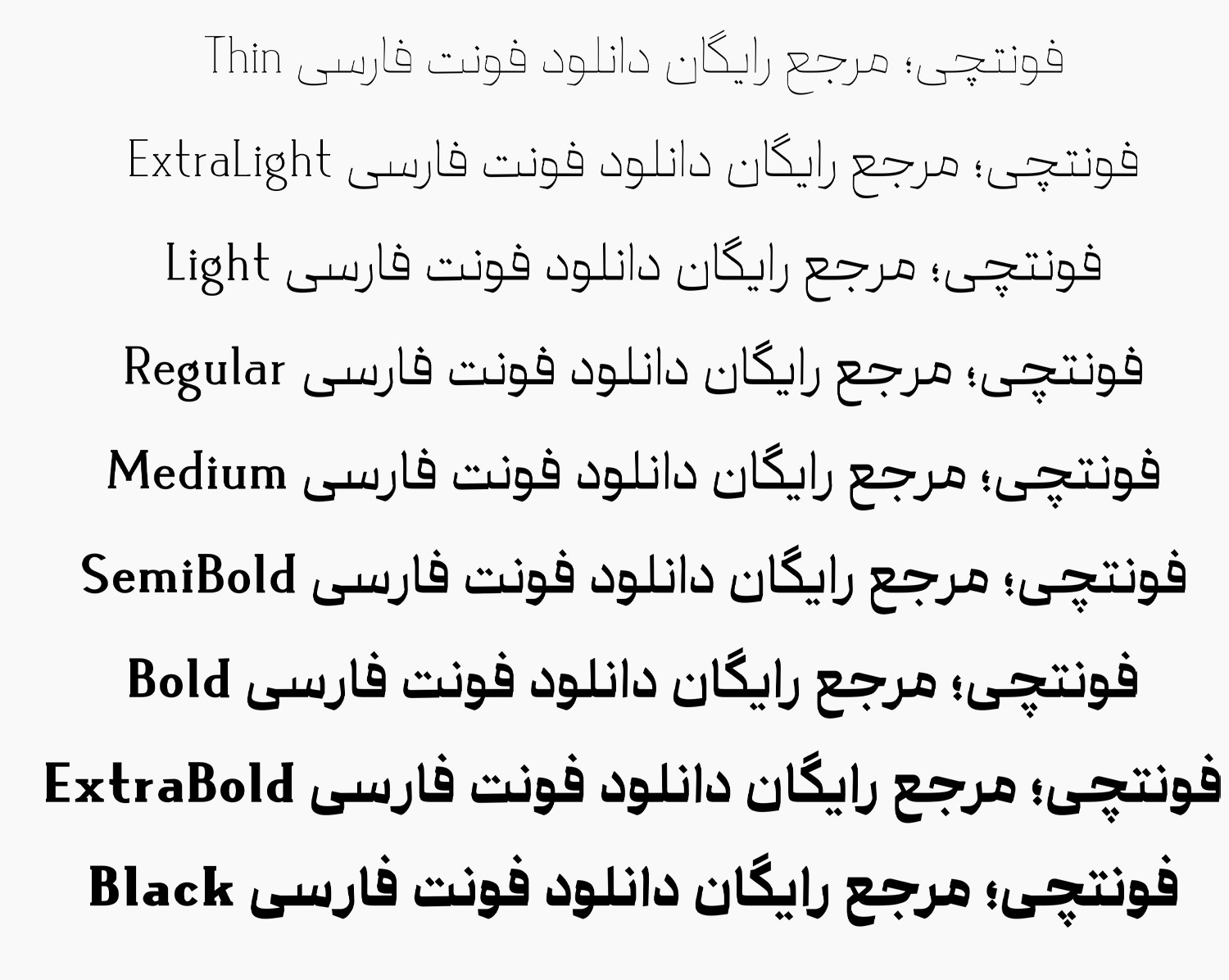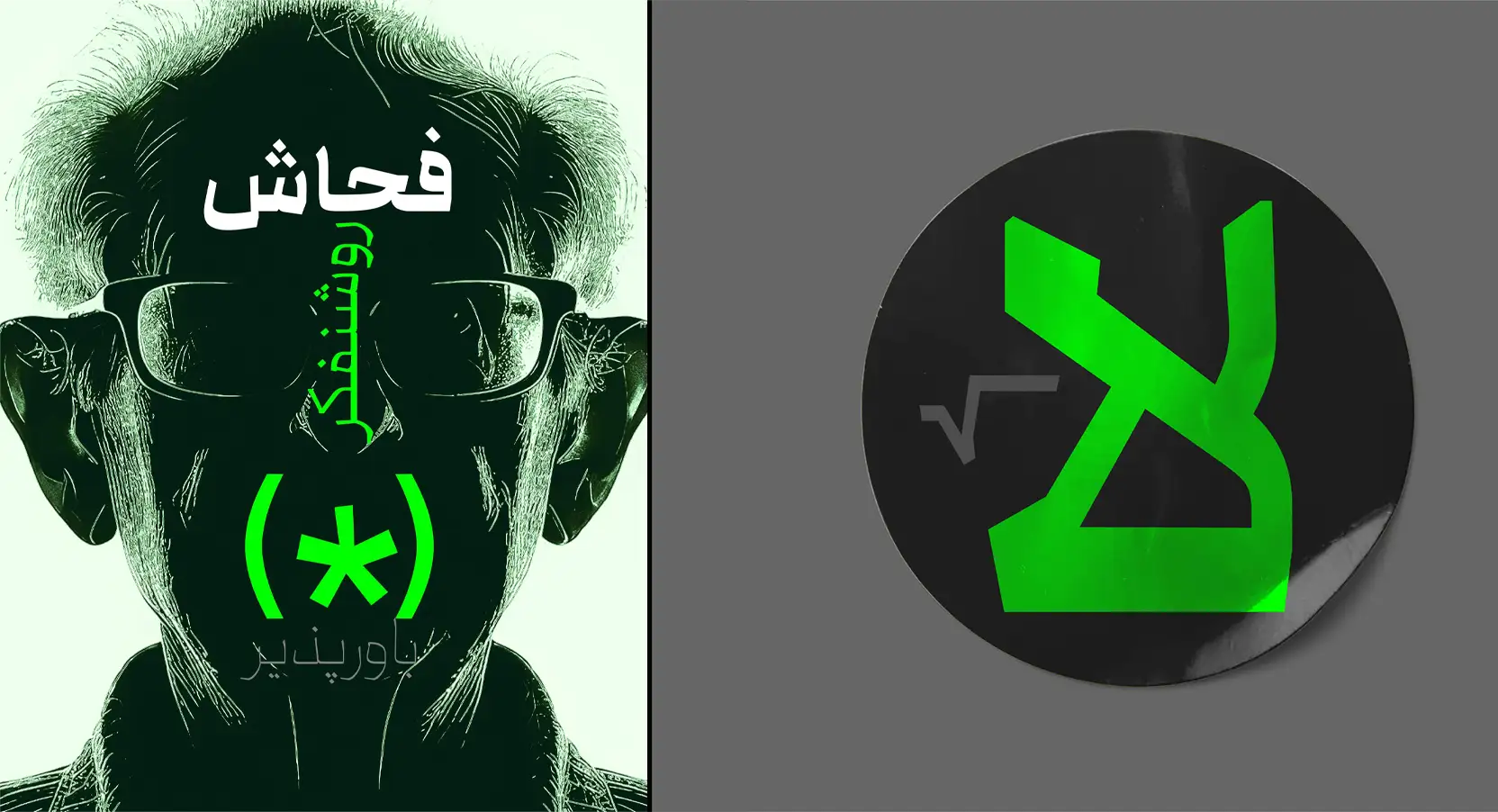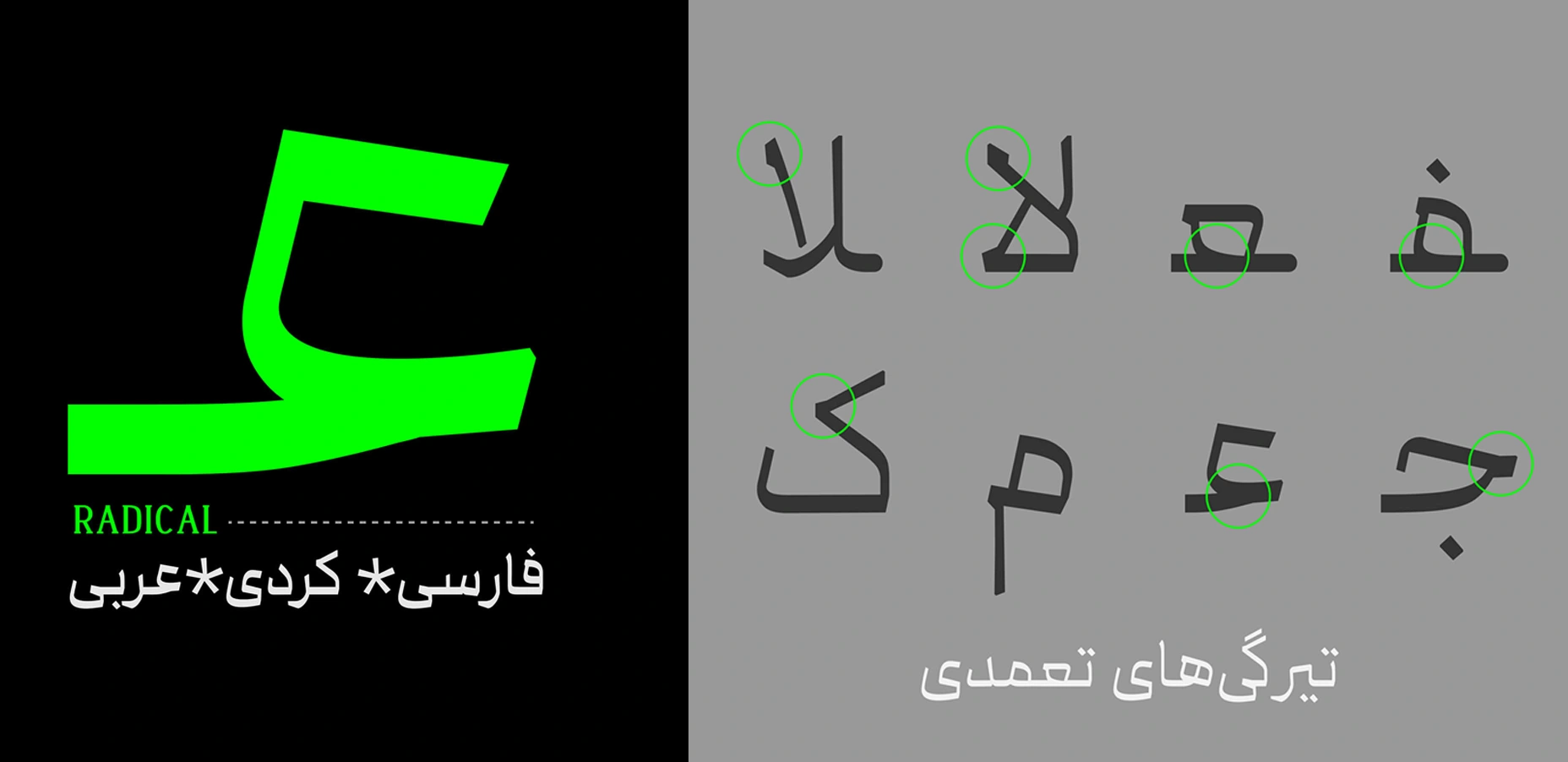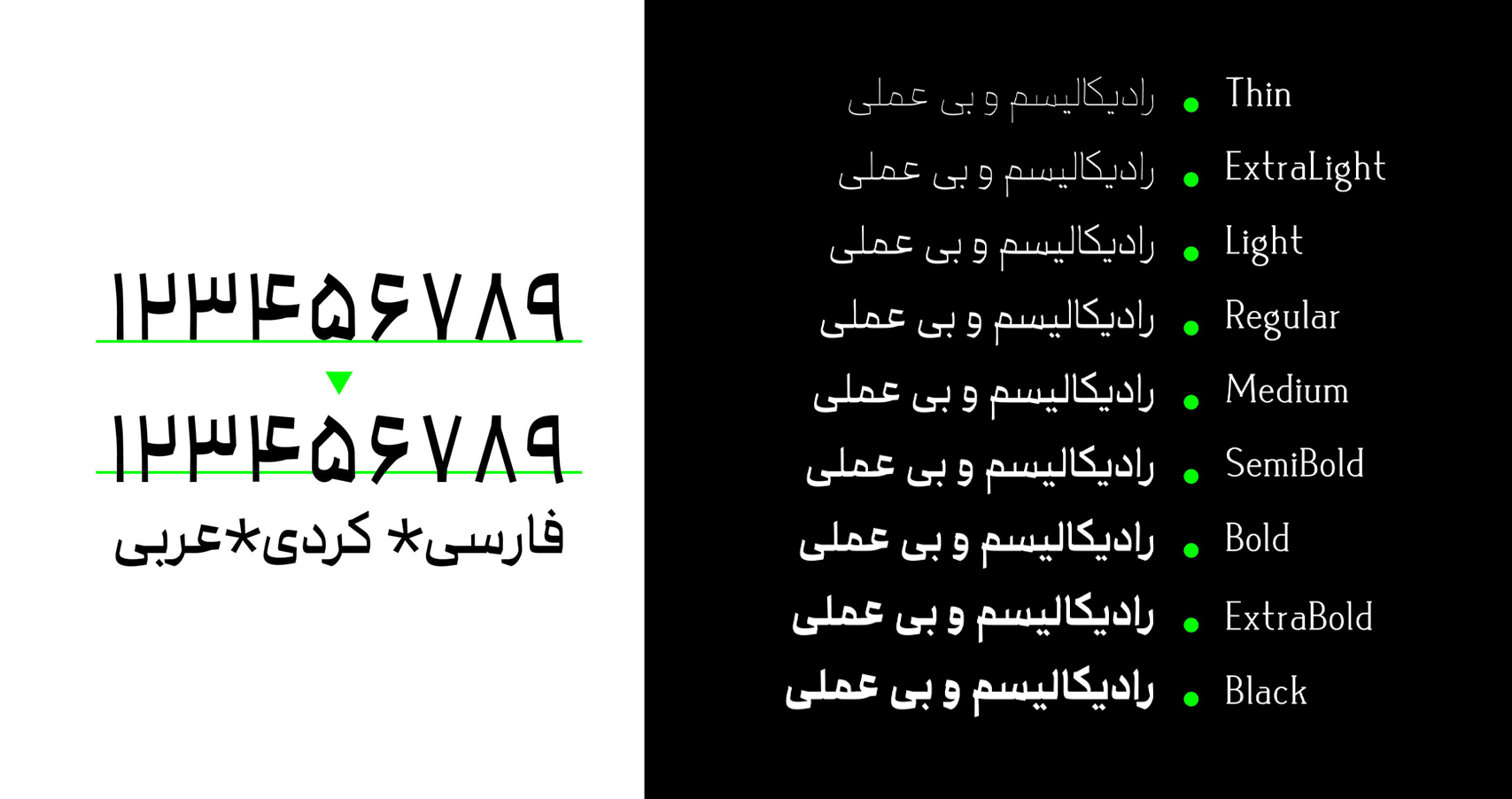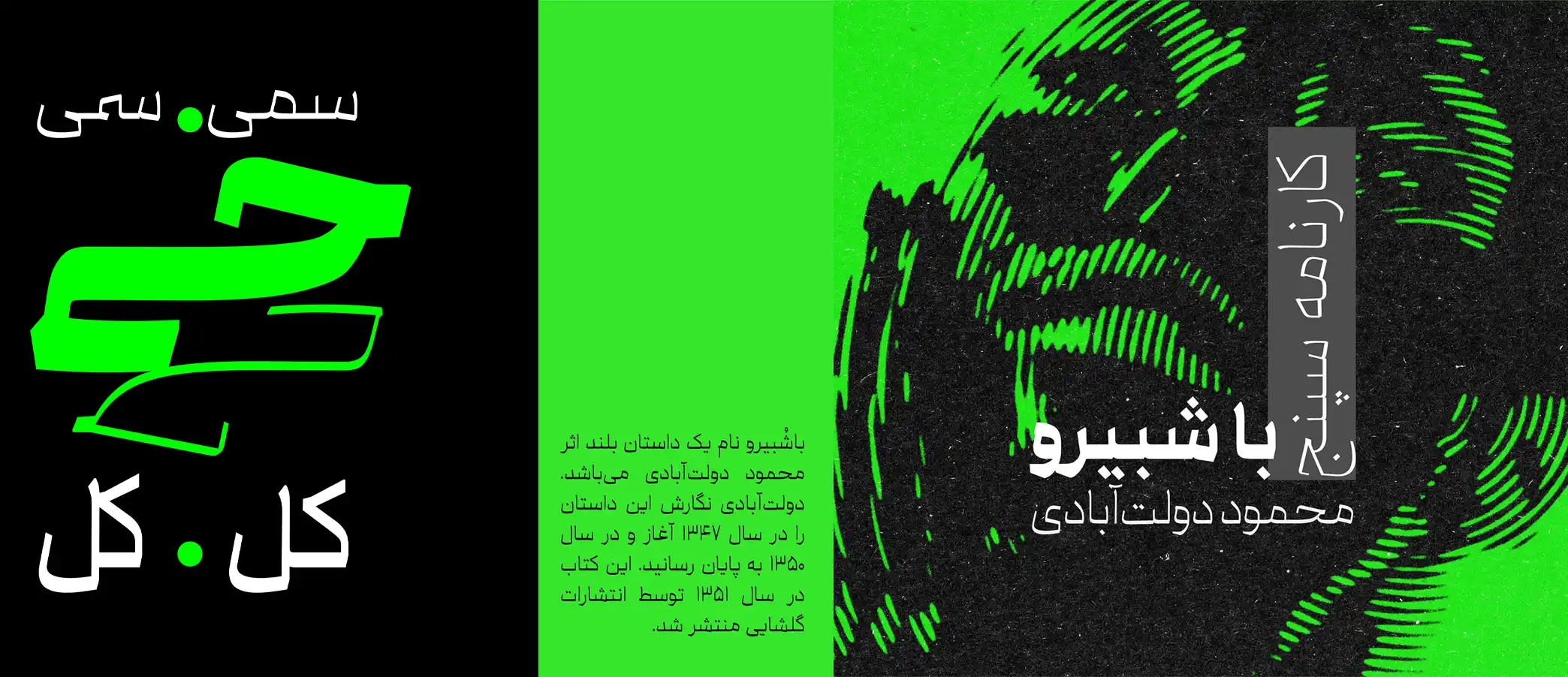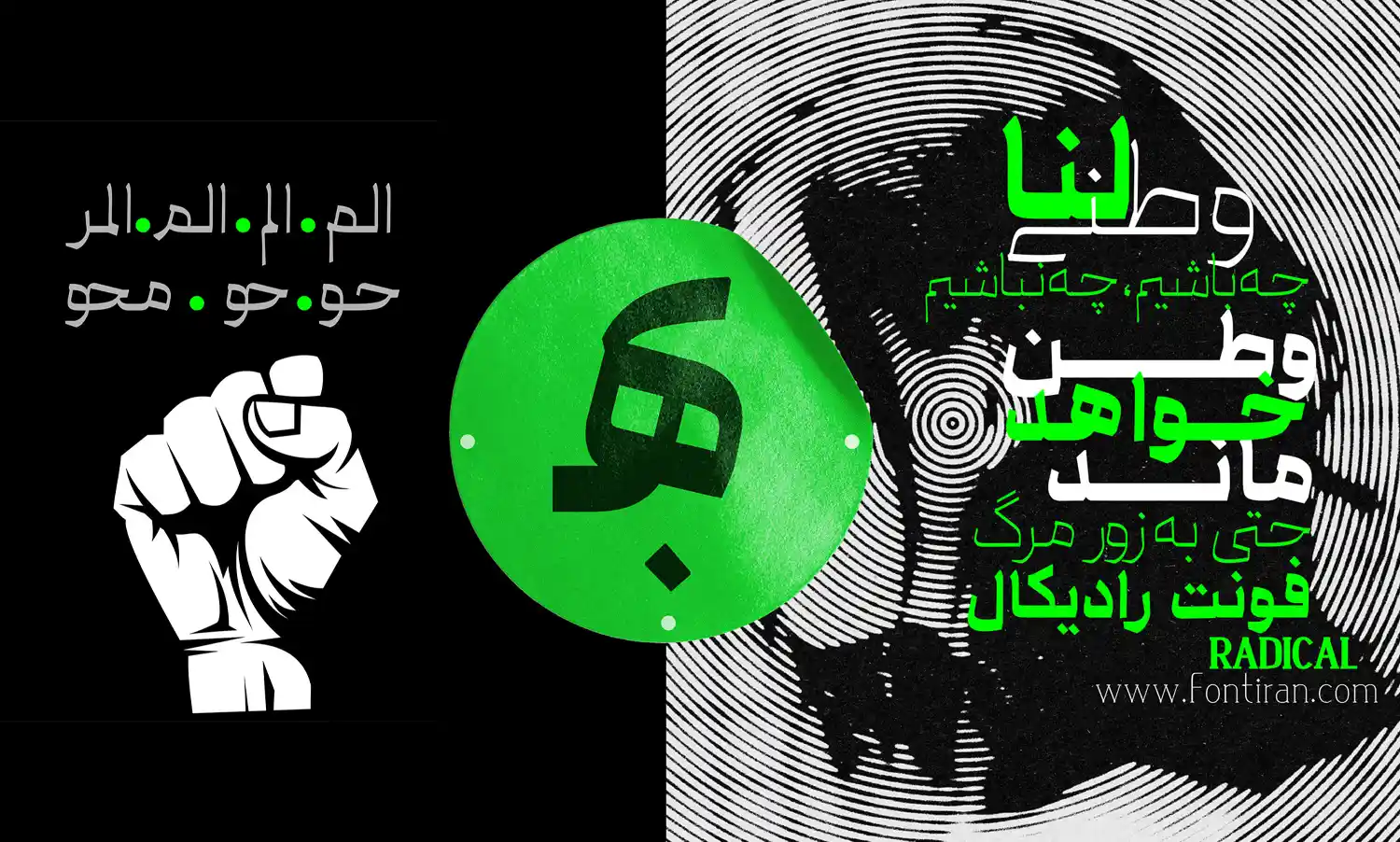
فونت رادیکال (Radical)
| طراح | مهرداد نوتاش |
فونت رادیکال (به انگلیسی: Radical) از سری فونتهای هندسی است که ظاهری نزدیک به خط نسخ دارد. این فونت که از ۹ وزن نازک تا سیاه را پشتیبانی میکند، برای استفاده در عناوین، تبلیغات، طراحی پوستر و کارهای گرافیکی انتخابی خارقالعاده است. فونت رادیکال رایگان نیست و در دو بسته مجزا با تنوع وزنی گوناگون قابل خریداری است.
مهرداد نوتاش این فونت نمایشی را با تمرکز بر روی پشتیبانی از زبانهای فارسی، عربی و کردی طراحی کرده است. ساختار فونت بهگونهای است که ضخامت حروف در خط کرسی دو برابر بوده و خود را بیشتر نشان میدهد. در ادامه با نقد و بررسی تخصصی این فونت جدید فارسی همراهمان باشید.
رادیکال (Radical) در نسخه اولیه خود با ۹ وزن (Thin، Extralight، Light، Regular، Medium، SemiBold، Bold، ExtraBold، Black) عرضه شده است.
طراحی فونت رادیکال بر پایه هندسه استوار است و شباهتهایی به خط نسخ سنتی دارد، اما ظاهر مدرن و جسورانه دنیای امروز در آن تنیده شده است. تنه حروف ضخامتی تقریبا دو برابر حد معمول قلمهای استاندارد را داراست؛ همین امر ظاهری محکم و سنگین به حروف داده است، بهویژه در خط کرسی. گویی طراح عمدا حروف را در چارچوب کلاسیک نسخ اسیر کرده، اما با فاصله گرفتن از این چارچوب، حرکات قلم آزادتر، نامنظمتر و «رادیکالتر» میشود.
این رویکرد، فونتی ایجاد کرده که تیرگیهای عمدی (مانند سایههای مصنوعی در منحنیها) و ضخامتهای غیرمعمول (مثل پهنای متغیر در استروکها) را به عنوان ویژگیهای کلیدی خود برجسته میکند. نتیجه، یک تایپوگرافی منحصربهفرد است که از یکنواختی فونتهای رایج فارسی فاصله میگیرد و تمایزی بصری قوی ایجاد میکند.
لحن فونت، «صریح، جدی و رو راست» است. از اینرو برای استفاده در محیطهایی برای بیان مستقیم و بیپرده ایدهها مناسب است. این لحن از طریق با افزایش کنتراست در ضخامتها (به ویژه در وزنهای Bold و سنگینتر) و فرمهای هندسی تیز (مانند زوایای حاد در حروف مثل “ک” یا “ر”) تقویت میشود.
در مقایسه با فونتهای نمایشی دیگر فارسی مانند ایران سنس یا وزیر، رادیکال نرمی کمتری داشته و بیشتر ظاهری تهاجمی از خود نشان میدهد. شباهت به نسخ آن را برای پروژههای فرهنگی و سنتی مناسب میکند، اما رادیکالیسمش (مانند انحرافات عمدی از خط مستقیم در استروکهای افقی) آن را به ابزاری ایدهآل برای طراحیهای معاصر تبدیل میکند.
رادیگال؛ فونتی چند زبانه بر پایه حروف فارسی
عدم طراحی اختصاصی برای حروف لاتین (استفاده از فونت پیشفرض سیستم) یک محدودیت است، که فونت را عمدتا به محتوای فارسی، عربی و کردی محدود کرده است.
پشتیبانی از اعداد فارسی با افزودن نسخه مخصوص اعداد فارسی هک شده (فایل فونت مخصوص دارای اعداد فقط فارسی) و نسخه مخصوص بدون لاتین (بدون حروف و اعداد انگلیسی)، آن را برای پروژههای تمامفارسی ایدهآل میکند.
مثلا در طراحی اپلیکیشن موبایل یا وبسایتهای ایرانی که لزومی به استفاده از حروف لاتین نیست یا لااقل میخواهید حروف و اعداد لاتین با فونت دیگری باشد، میتوانید از این نسخههای مخصوص استفاده کنید تا رابط کاربری بهتری ایجاد کنید.
همچنین، پشتیبانی از زبانهای عربی و کردی انعطافپذیری بیشتری را برای طراحی، بهویژه در کارهای فرهنگی و ستی فراهم نموده است.
کاربردهای فونت رادیکال
رادیکال به طور خاص برای کارهای نمایشی و گرافیکی که جنبه جلب توجه دارند طراحی شده است. از عناوین بزرگ (Headlines) و لوگوها روی پوسترهای تبلیغاتی یا کاورهای کتاب گرفته تا استفاده از وزنهای میانه در استوریهای اینستاگرام یا تبلیغات بنری درون سایت!
به لطف ضخامت دوگانهای که در تنه حروف این فونت ایجاد شده، خوانایی در اندازههای بزرگ حفظ شده و در عین حال باعث خلق تیرگیهای عمدی در عمق محتوای بصری ایجاد میکند؛ این مسئله باعث نمایشیتر شدن فونت شده و ظاهر آن را از پسزمینههای شلوغ متمایز میسازند.
برای مثال، در وزن سیاه فونت رادیکال، حروفی مانند «ف» یا «ق» با فرمهای حجیم و سایهدار، حس قدرت و جدیت را القا میکنند، که برای کمپینهای تبلیغاتی با جنبههای اجتماعی و فرهنگی (مانند شعارهای رادیکال و مستقیم) عالی است. در حالی که وزنهای نازکتر مانند Thin، کنتراست را با پسزمینههای روشن بیشتر نمایان میکند که برای تیترهای ظریفتر در طراحیهای مینیمال مناسب هستند.